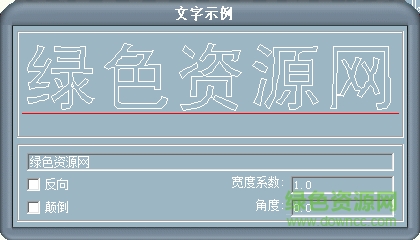
bldjgbkfs字體是一款非常經(jīng)典的cad字體,這類字體在cad中運(yùn)用十分廣泛,很多圖紙現(xiàn)在都用的這個(gè)字體,確實(shí)看起來這個(gè)字體很不錯(cuò),而且線條也非常的優(yōu)美,而且在畫圖紙過程中來這款字體字形流暢,有需要的就來綠色資源網(wǎng)下載吧!
shx是CAD軟件中專用的字體,都是autocad專用專有的字體,通過這些字體能夠在CAD中進(jìn)行輸入和寫文字,讓用戶更好的標(biāo)注CAD中的圖紙。